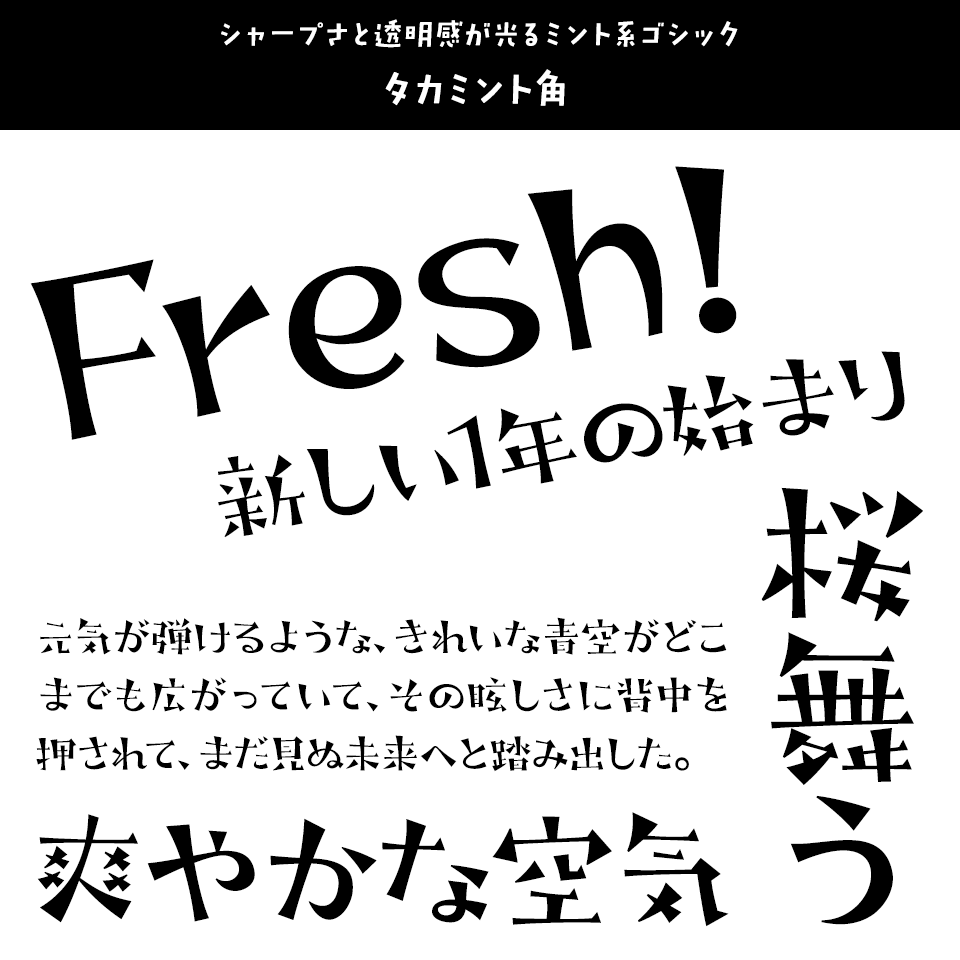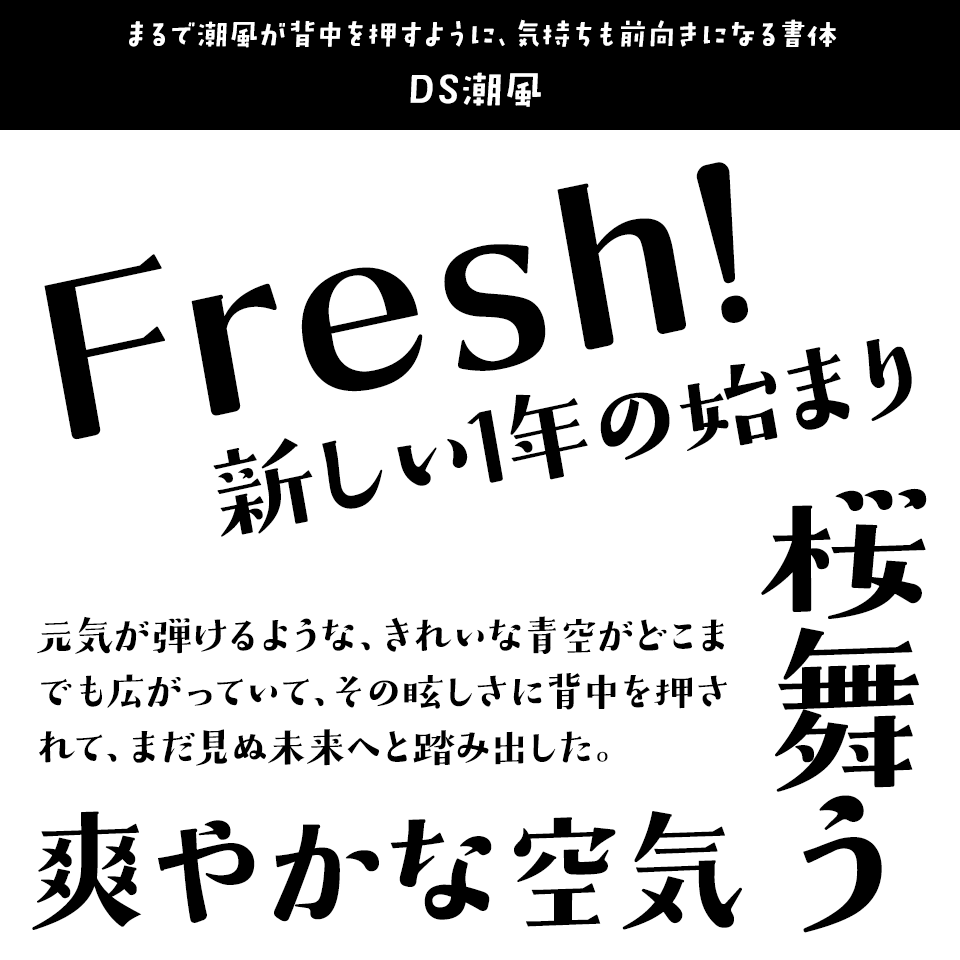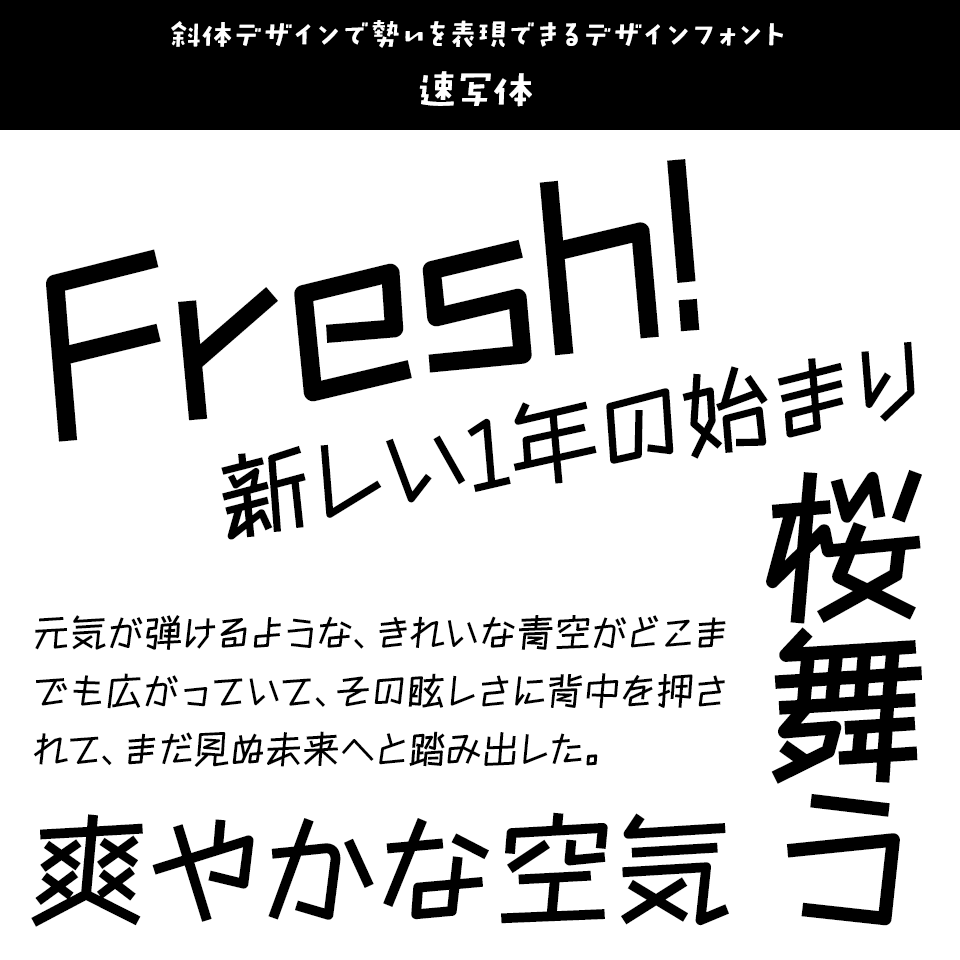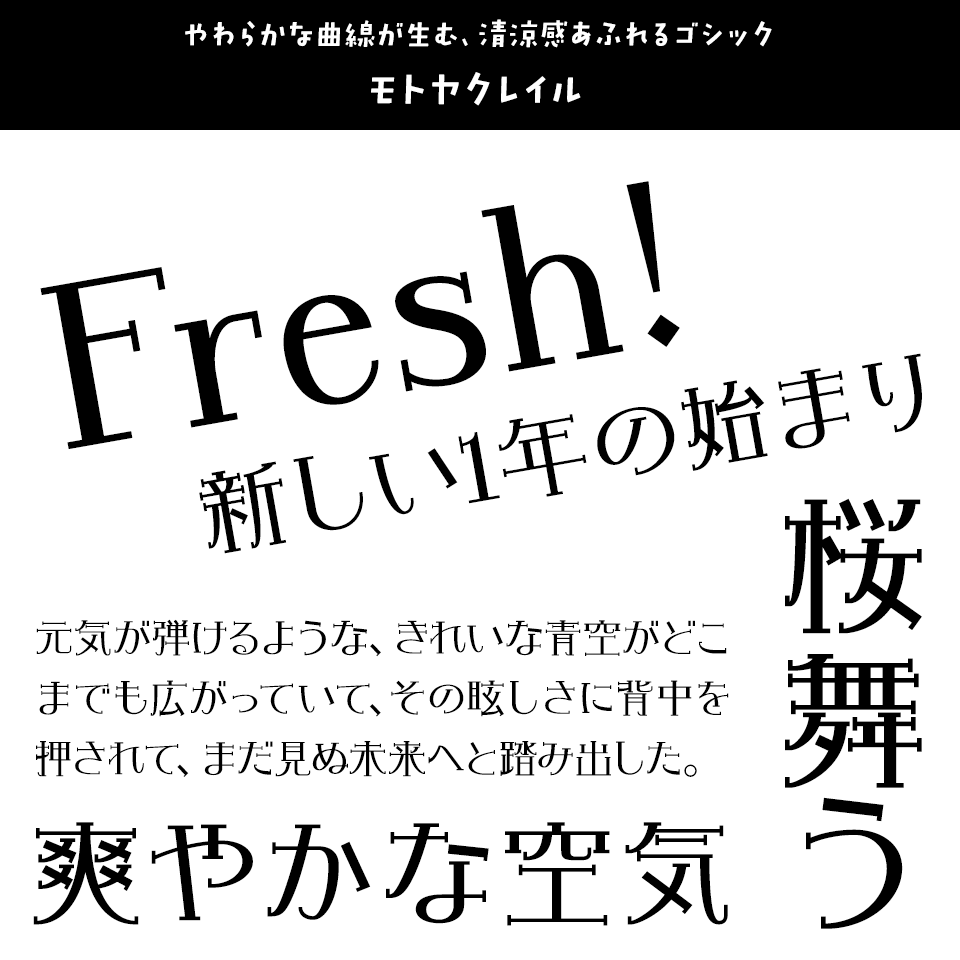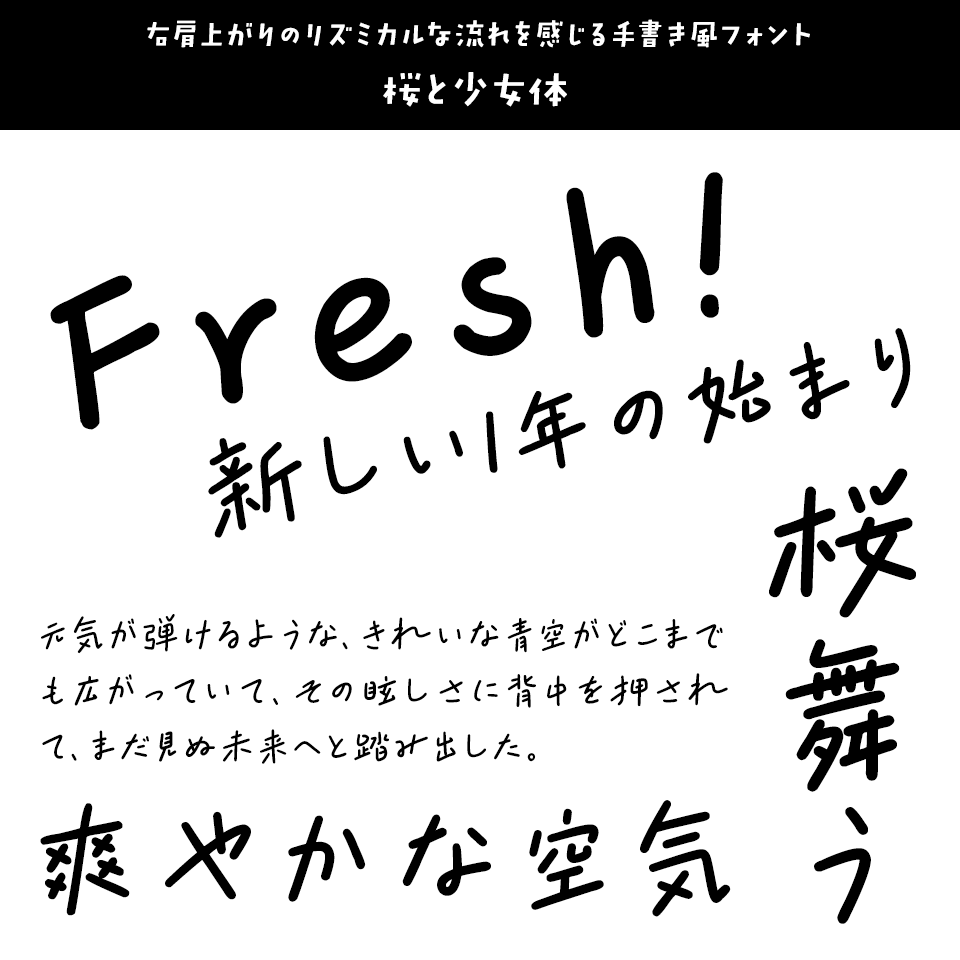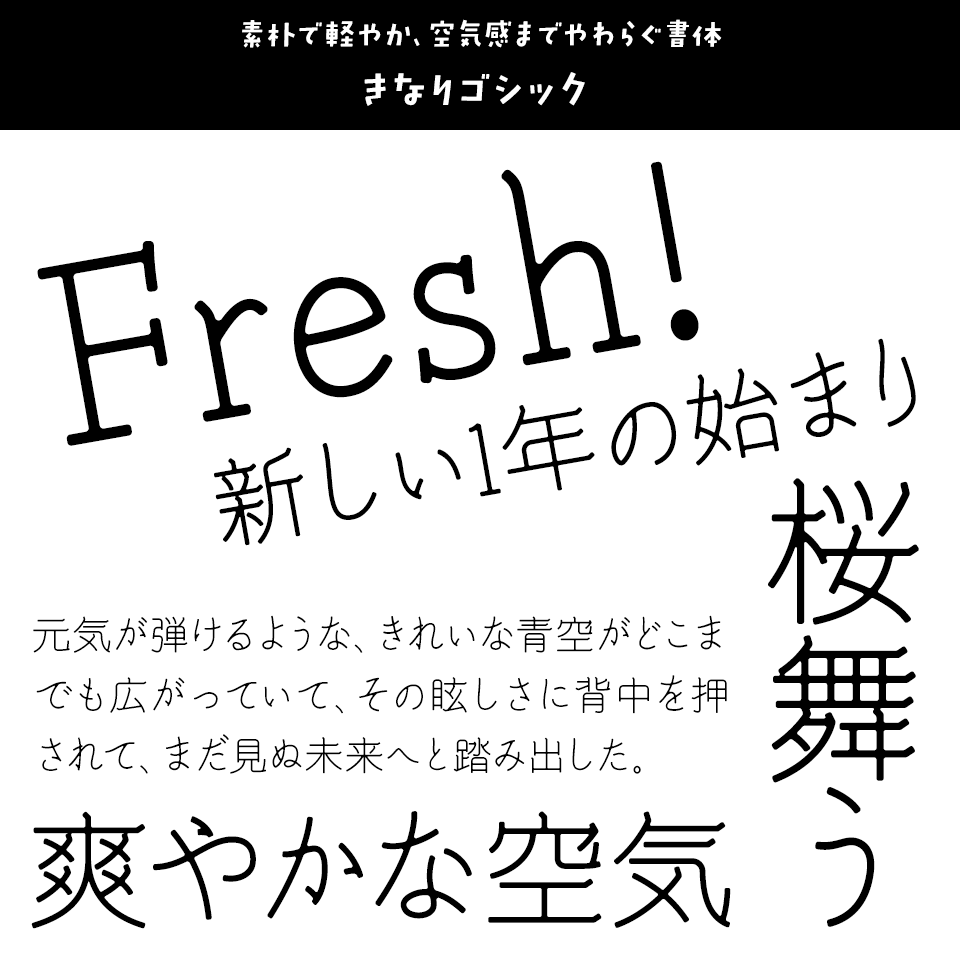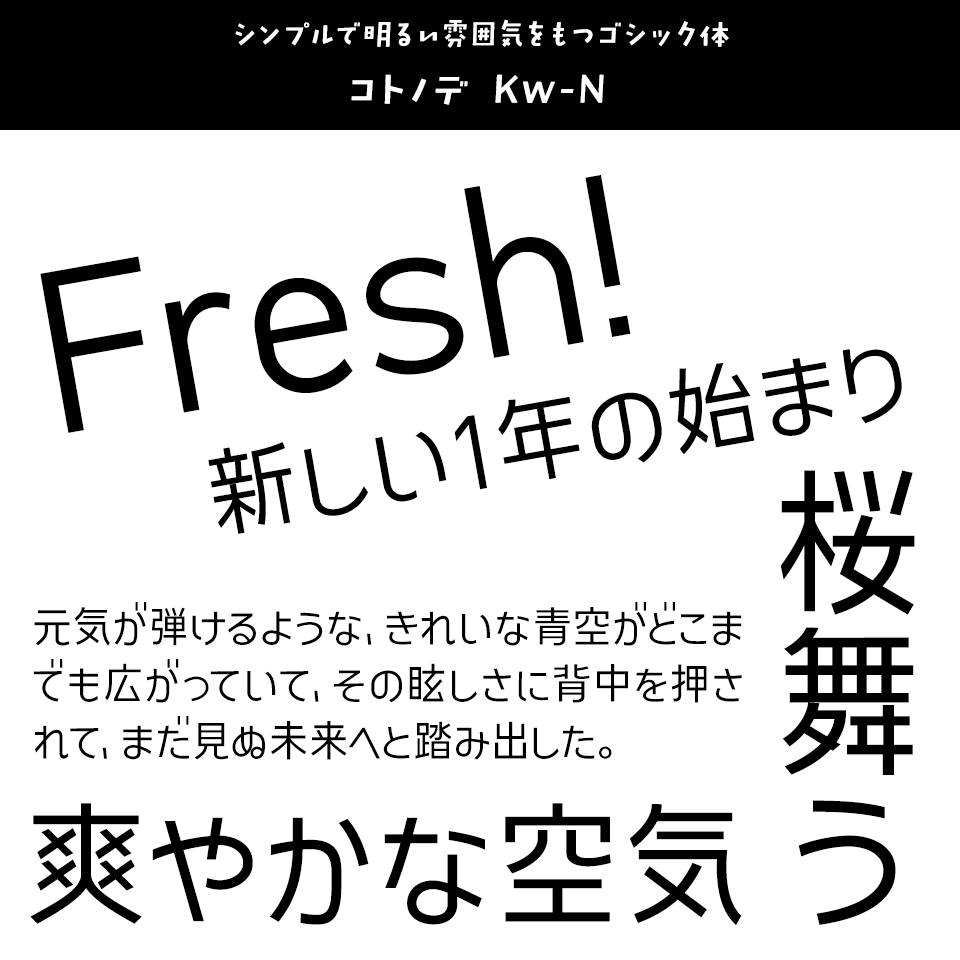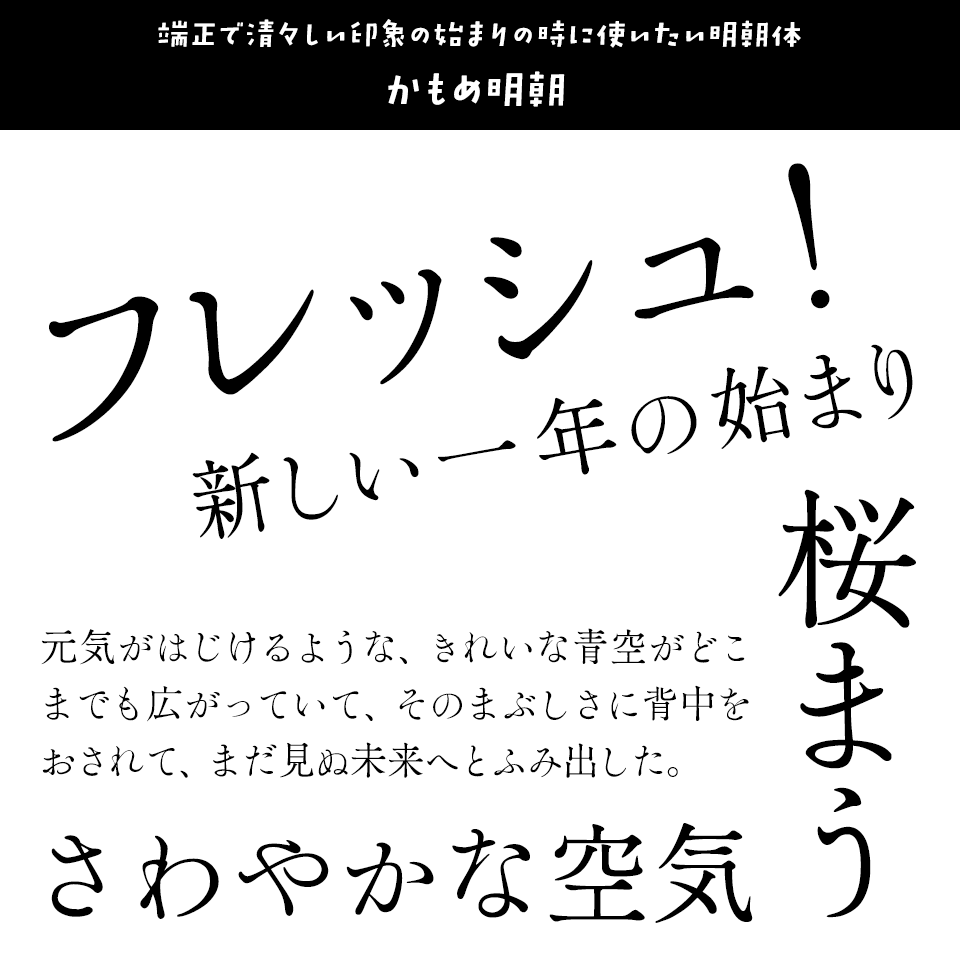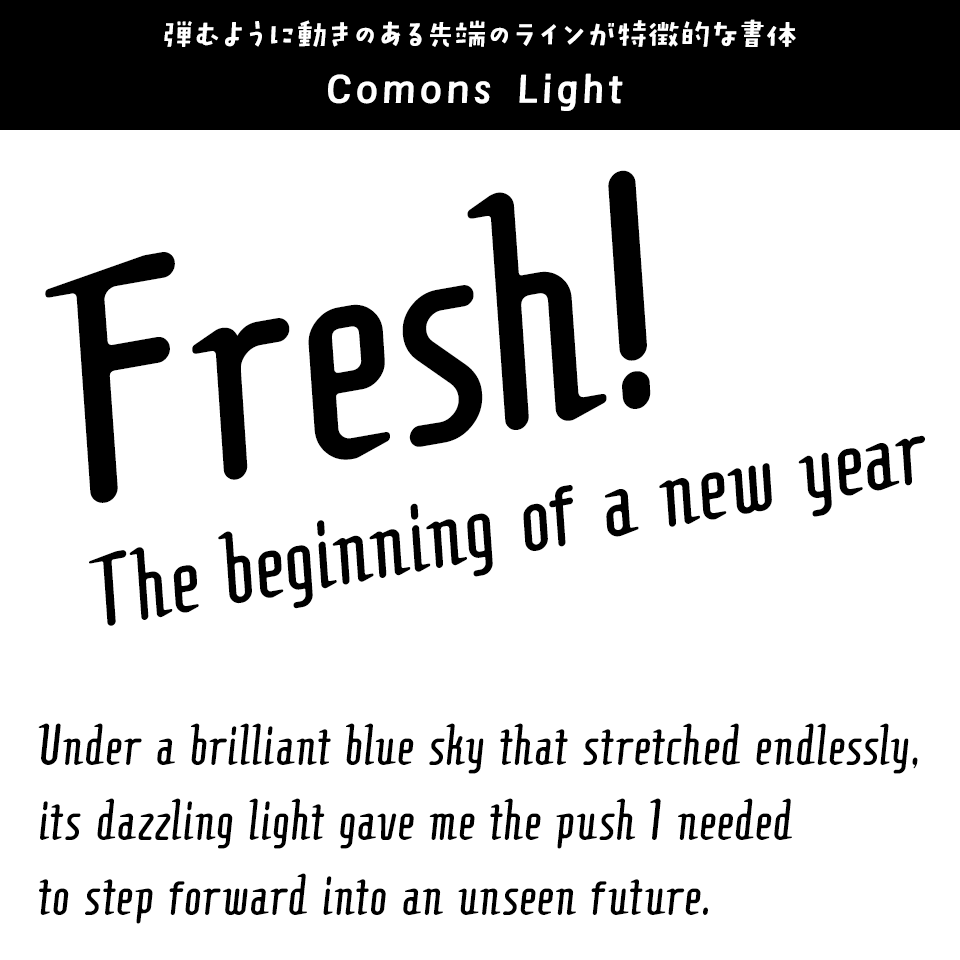
「フレッシュ」に合うフォント:特化型 目的別フォントガイド #182
「フレッシュ」に合うフォント タカミント角
シャープさと透明感が光るミント系ゴシック
▶タカミント角【タカ書体】
「フレッシュ」に合うフォント タカミント角
タカミント角は、角ゴシックの持つ端正さに、軽やかなリズムを加えた爽快な書体。すっきりとした字面と均整の取れた設計が、クリーンで前向きな印象を演出します。
「フレッシュ」に合うフォント DS潮風
まるで潮風が背中を押すように、気持ちも前向きになる書体
▶DS潮風【七種泰史/デザインシグナル】
「フレッシュ」に合うフォント DS潮風
波の音、風の音。波しぶき、潮の香り。波打ち際での自然の風をイメージした書体です。
「フレッシュ」に合うフォント 速写体
斜体デザインで勢いを表現できるデザインフォント
▶速写体【楽フォント】
「フレッシュ」に合うフォント 速写体
文字の結び目は優雅で、ストロークの先端と末端の変化は安定感を求める、滑らかで力強く美しいリズム感に満ちる書体です。斜体のデザインにより文字の印象はエレガントで、美しい現代的な感じを与えます。
「フレッシュ」に合うフォント モトヤクレイル
やわらかな曲線が生む、清涼感あふれるゴシック
▶モトヤクレイル【モトヤ】
「フレッシュ」に合うフォント モトヤクレイル
モトヤクレイルは、丸みを帯びたやさしい骨格と、軽やかな線質が印象的なゴシック体。堅すぎず甘すぎない絶妙なバランスが、紙面や画面に“すっきりとした新鮮さ”をもたらします。
「フレッシュ」に合うフォント 桜と少女体
右肩上がりのリズミカルな流れを感じる手書き風フォント
▶桜と少女体【楽フォント】
「フレッシュ」に合うフォント 桜と少女体
ゆったりした気分で、つるつるした紙に細い平筆で描かれた書体。メリハリがあり、字が右上に傾いてすっきりとしています。息をしている間に自由な感覚が生まれてくるような視覚表現力があります。
「フレッシュ」に合うフォント F1000-アンダンテ F2 Regular
音楽のように、軽やかなリズムを感じさせる書体
▶F1000-アンダンテ F2 Regular【FONT1000】
「フレッシュ」に合うフォント F1000-アンダンテ F2 Regular
その名の通り軽やかなテンポをまとい、文字に心地よいリズムを生み出します。使うほどに音楽を奏でるかのような高揚感が広がり、弾むような空気をもたらします。躍動感のあるフォルムが、見る人の気持ちまで明るく前向きにしてくれる書体です。
「フレッシュ」に合うフォント きなりゴシック
素朴で軽やか、空気感までやわらぐ書体
▶きなりゴシック【ヤマナカデザインワークス】
「フレッシュ」に合うフォント きなりゴシック
きなりゴシックは、ナチュラルで肩の力が抜けた表情が魅力のデザインゴシック。整いすぎないフォルムが、自然体のやさしさとフレッシュな抜け感を生み出します。
「フレッシュ」に合うフォント コトノデ Kw-N
シンプルで明るい雰囲気をもつゴシック体
▶コトノデ Kw-N【コトノハワークス】
「フレッシュ」に合うフォント コトノデ Kw-N
シンプルで可愛い。それでいて読みやすいデザインゴシック体。上下にやや広がる設計により、タイトルや見出しで組んだ際に自然なリズムが生まれ、シンプルなレイアウトでも表情豊かな仕上がりに。可愛らしさと視認性を両立した、使い勝手のよい書体です。
「フレッシュ」に合うフォント かもめ明朝
端正で清々しい印象の始まりの時に使いたい明朝体
▶かもめ明朝【文字魚/Typographish】
「フレッシュ」に合うフォント かもめ明朝
築地四号系で昭和初期に作られたであろう金属活字から着想を得て作られました。金属活字特有の文字のふくよかさを強調してやわらくて、温かみのある印象になっています。
「フレッシュ」に合うフォント Comons Light
弾むように動きのある先端のラインが特徴的な書体
▶Comons Light【CFONT】
「フレッシュ」に合うフォント <strong>Comons Light</strong>
セリフに特徴を持たせ、縦横の比率を大きく動きのあるフォントにしました。お得な109フォントセットもあります。